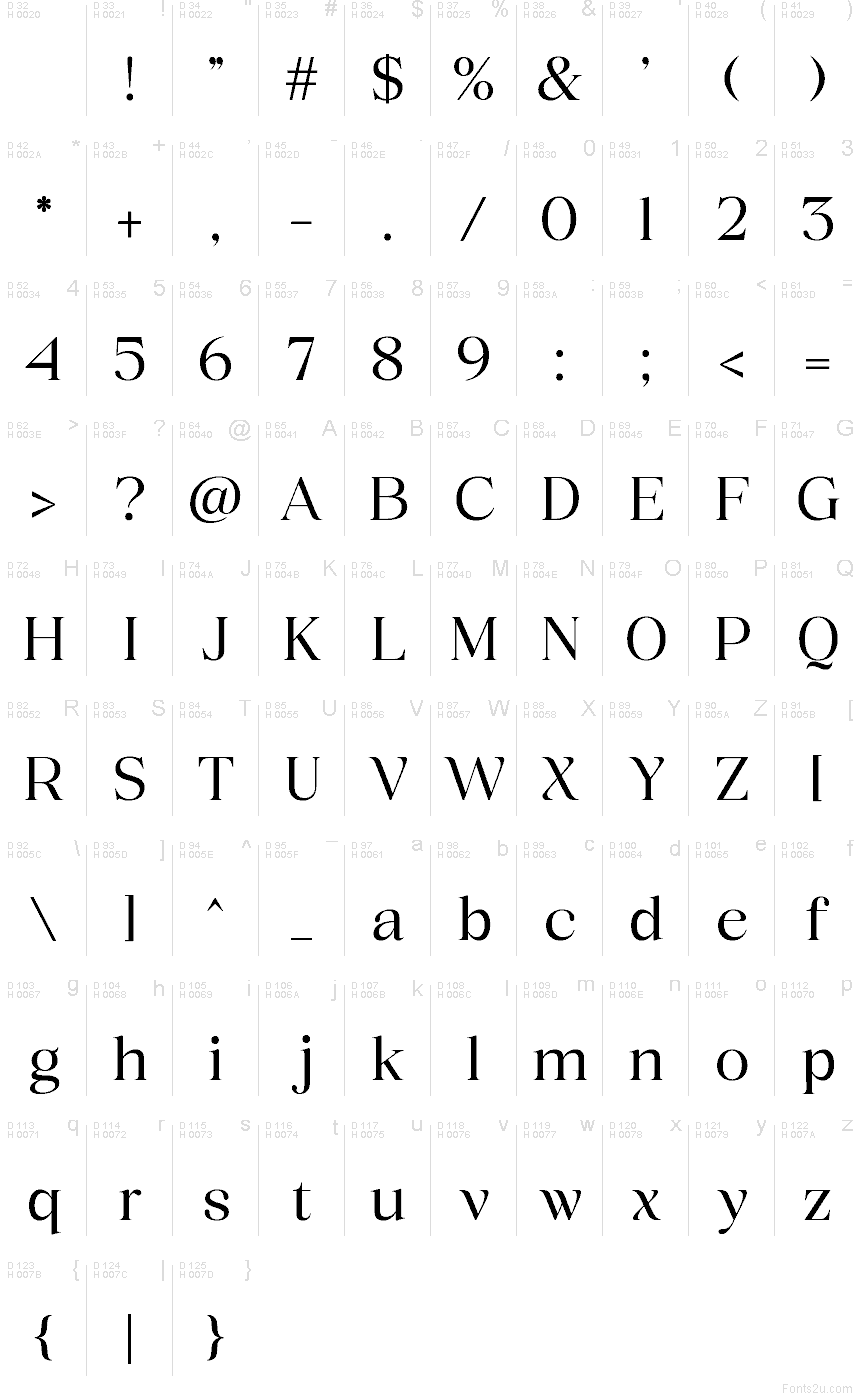
Scaver Light, creata da Glyphminds Studios, è un carattere serif gratuito ad alto contrasto con un mood editoriale che strizza l'occhio al mondo della moda. Le lettere mescolano linee sottili, curve ampie e dettagli angolari, rendendo il carattere raffinato ma mai rigido.
È perfetto per branding, copertine di riviste, packaging di boutique, inviti e titoli dove serve un tocco di drammaticità senza diventare eccessivamente ornamentale. Essendo un font gratuito, funziona bene anche per titoli brevi, bozze di loghi e monogrammi, specialmente quando si vuole valorizzare quel contrasto arioso e il tratto leggermente calligrafico visibile nelle lettere.